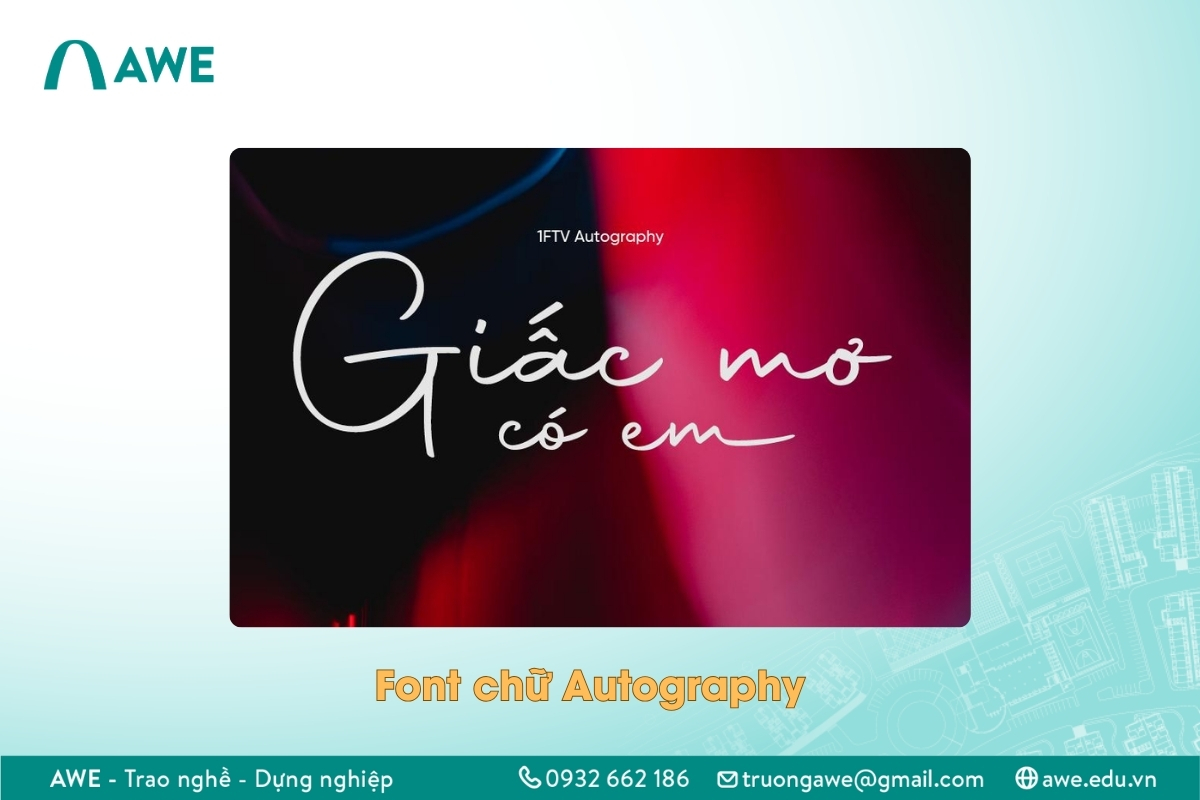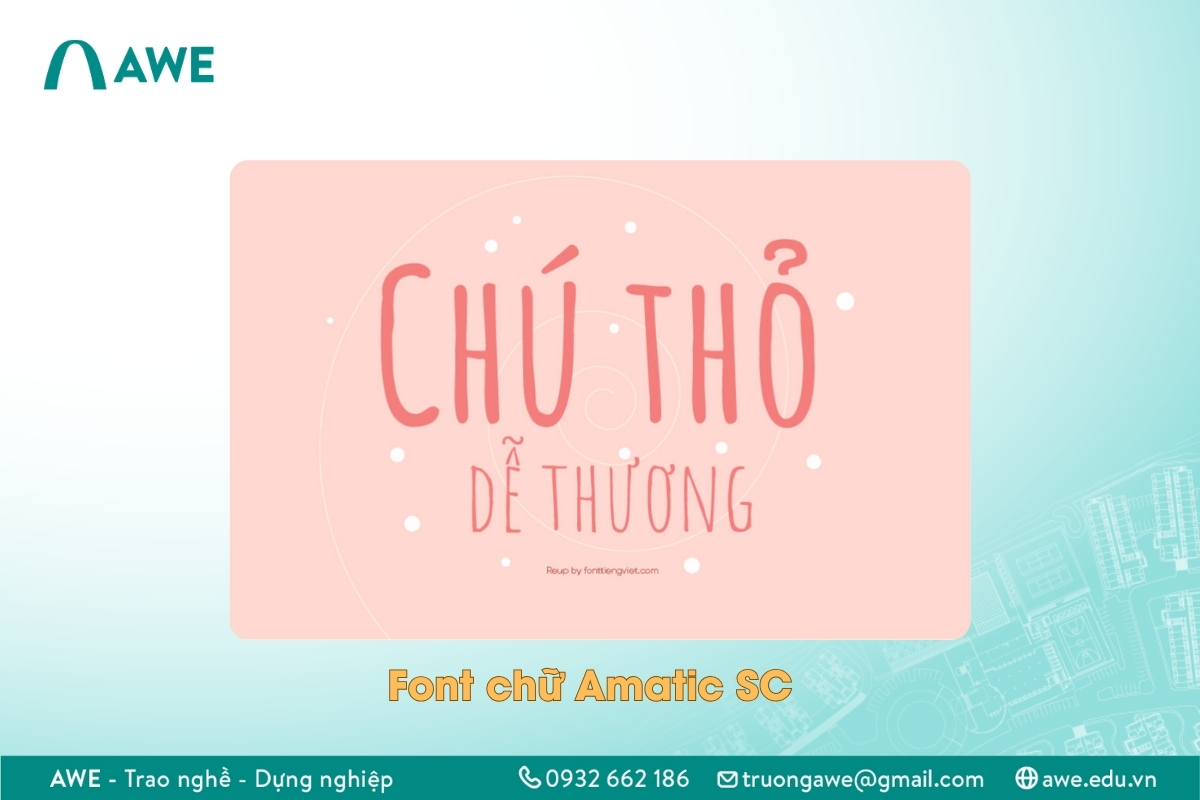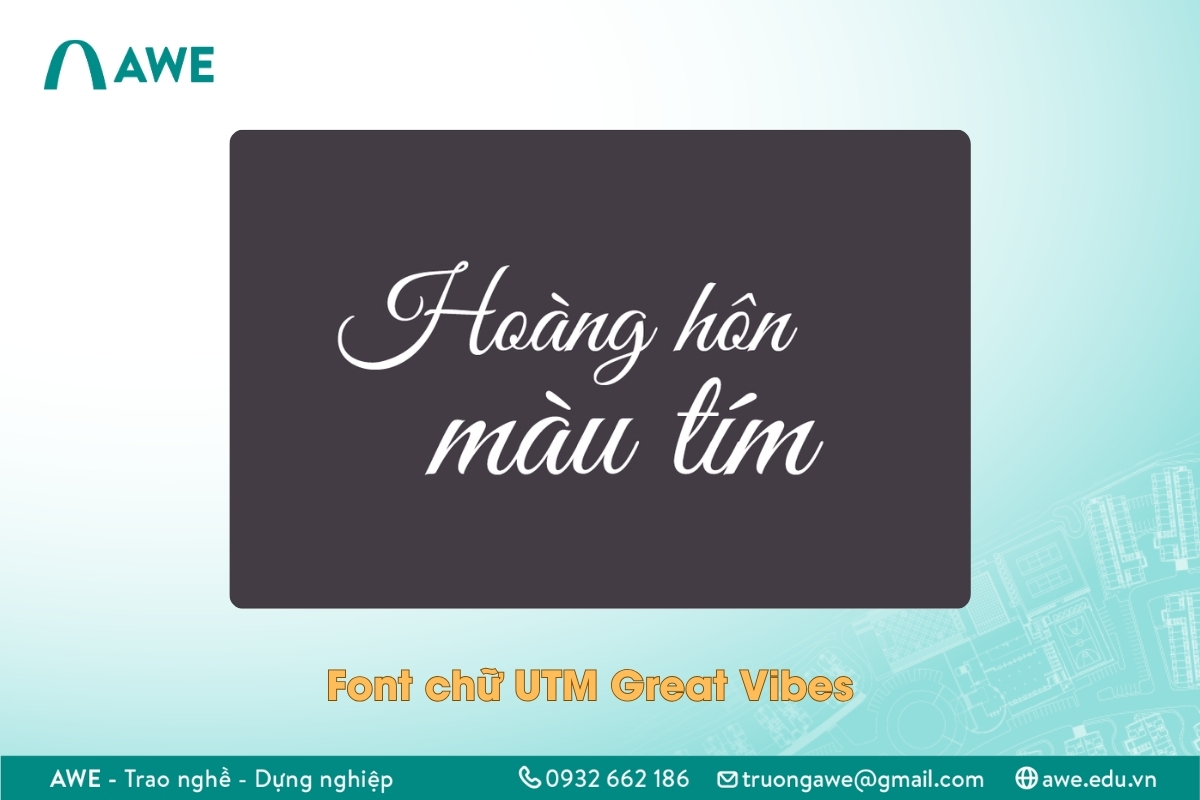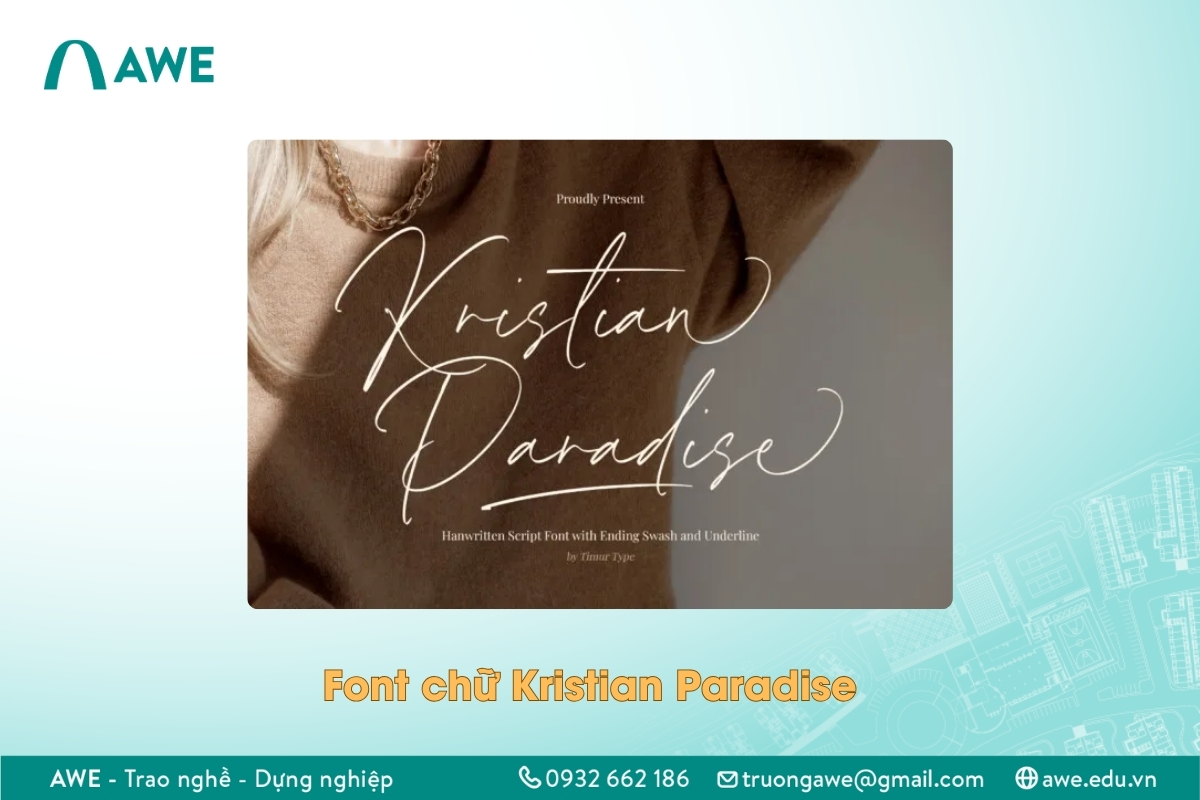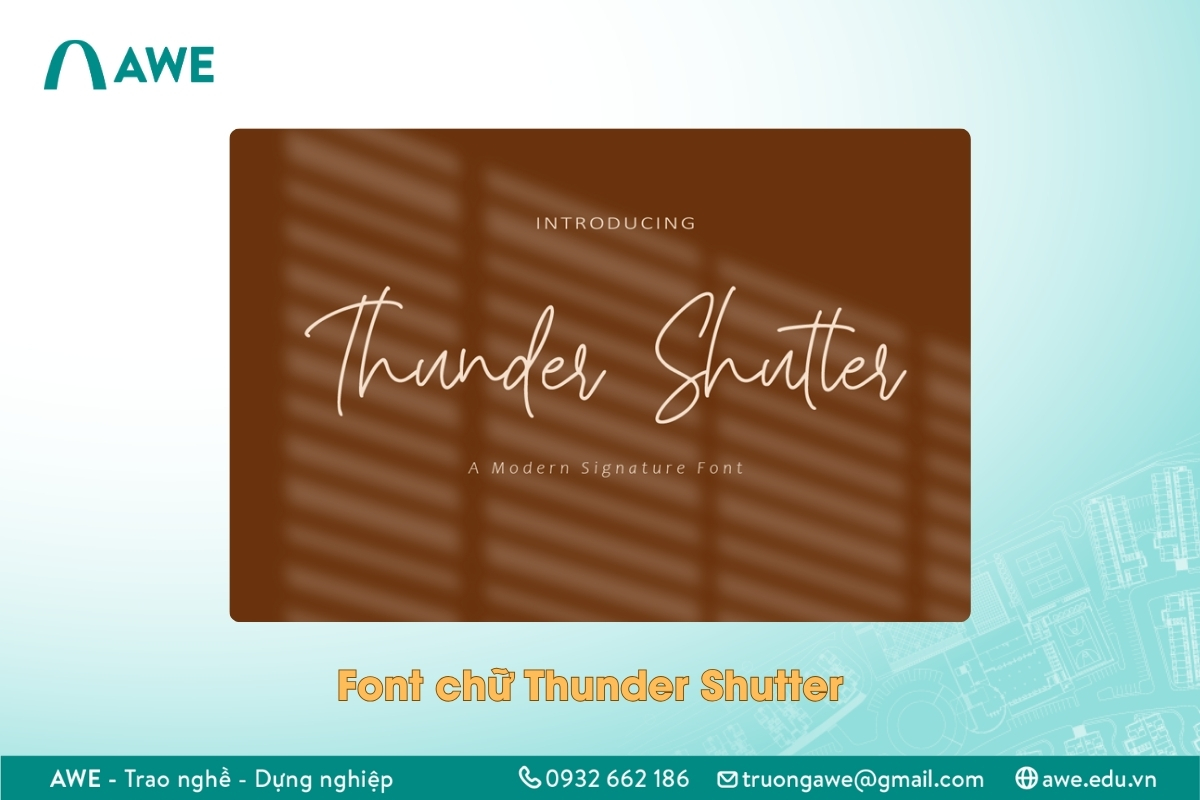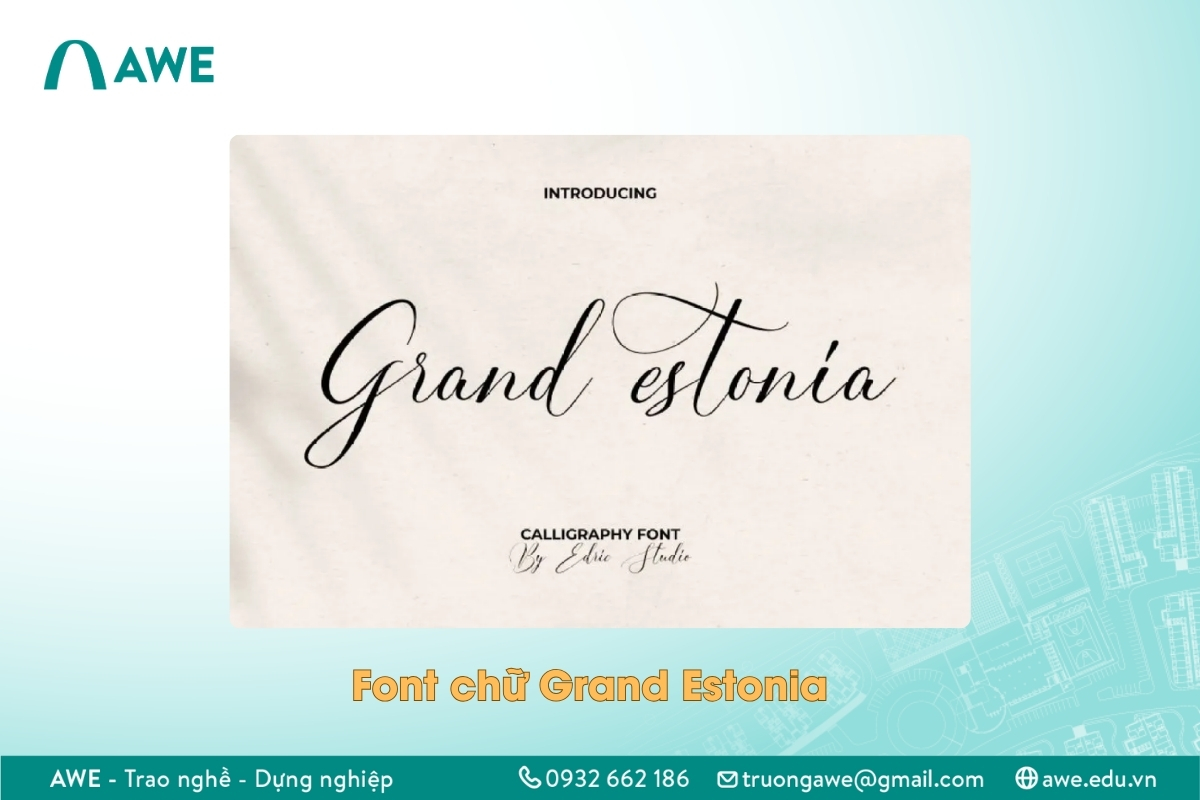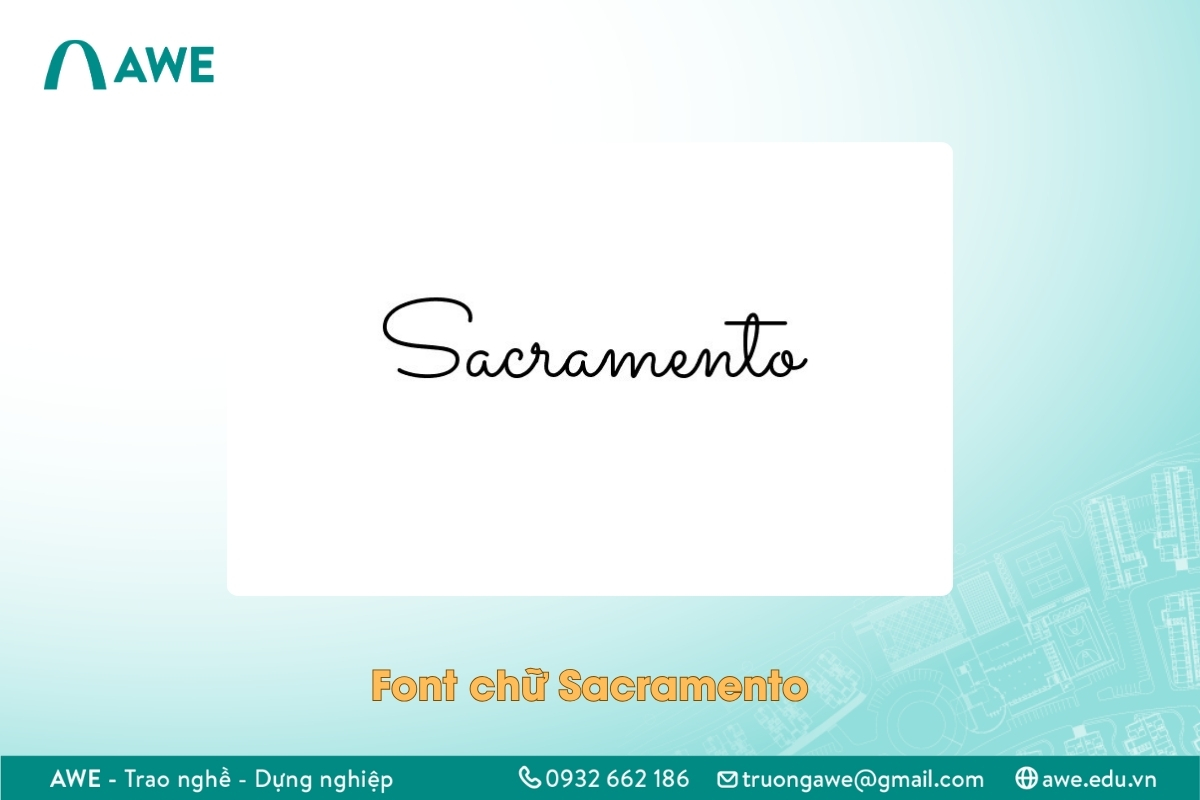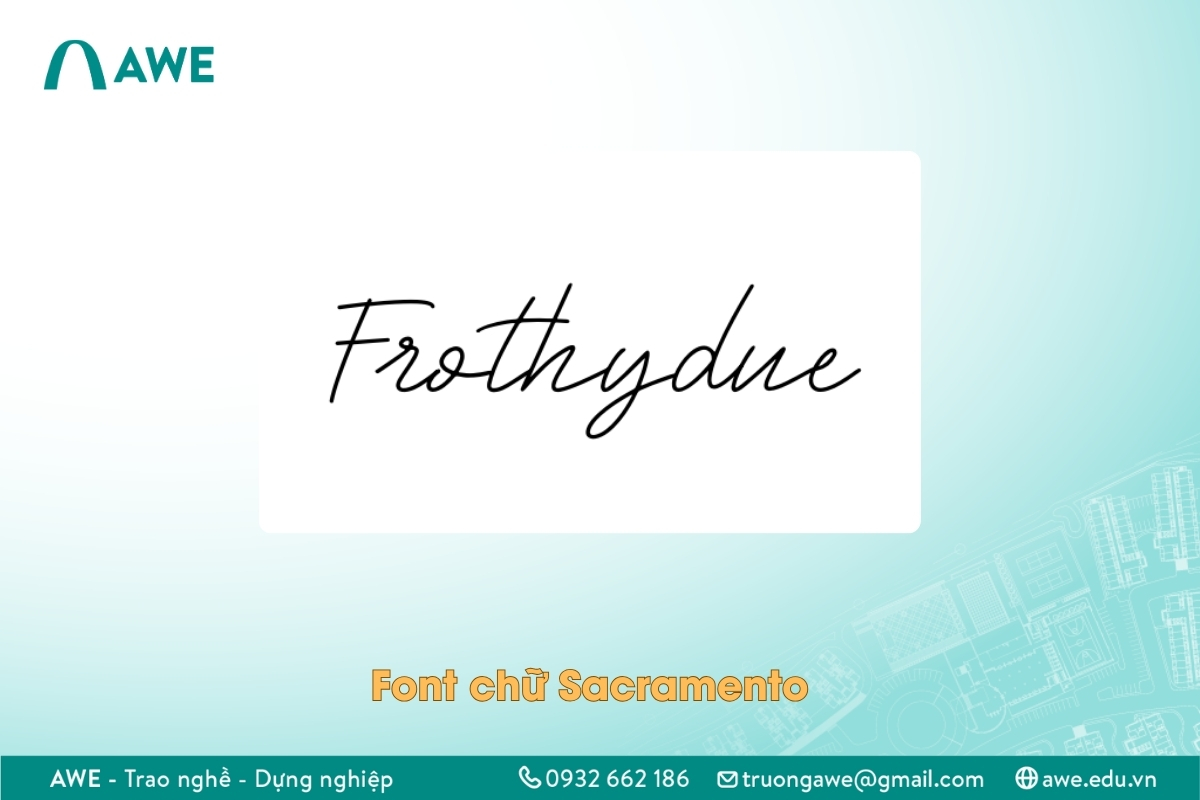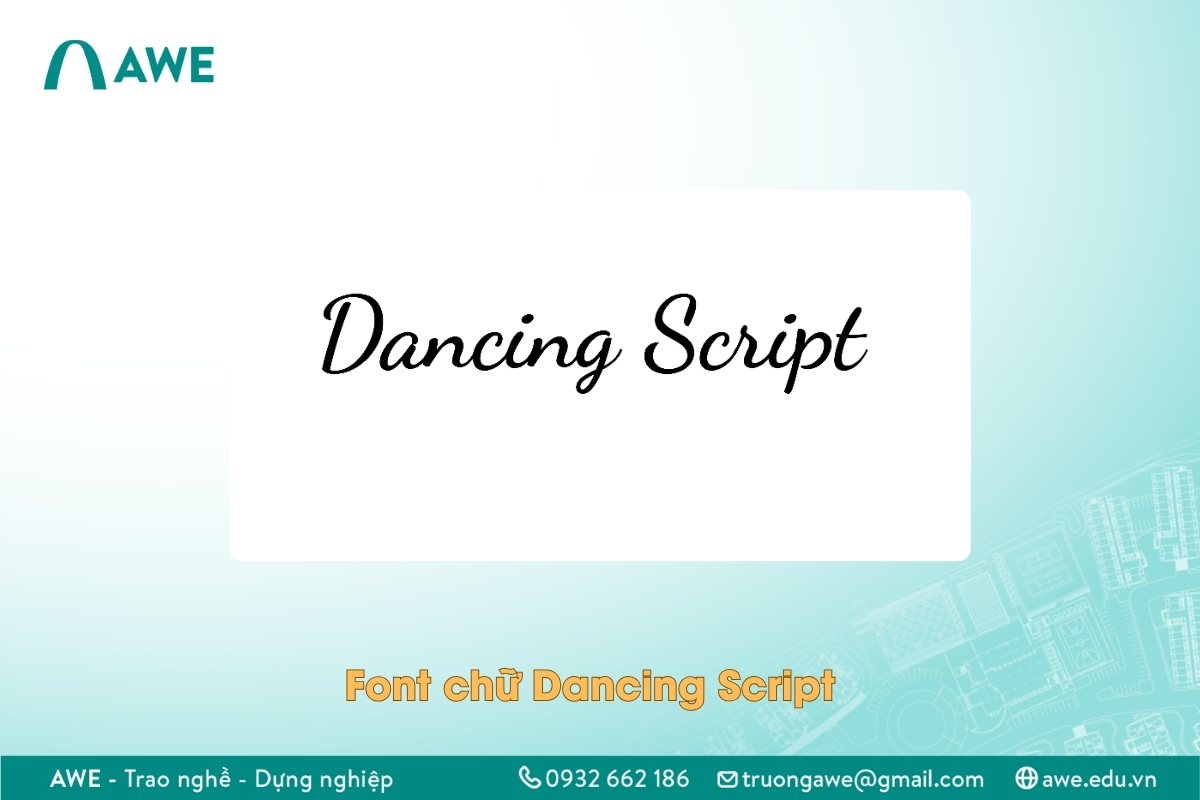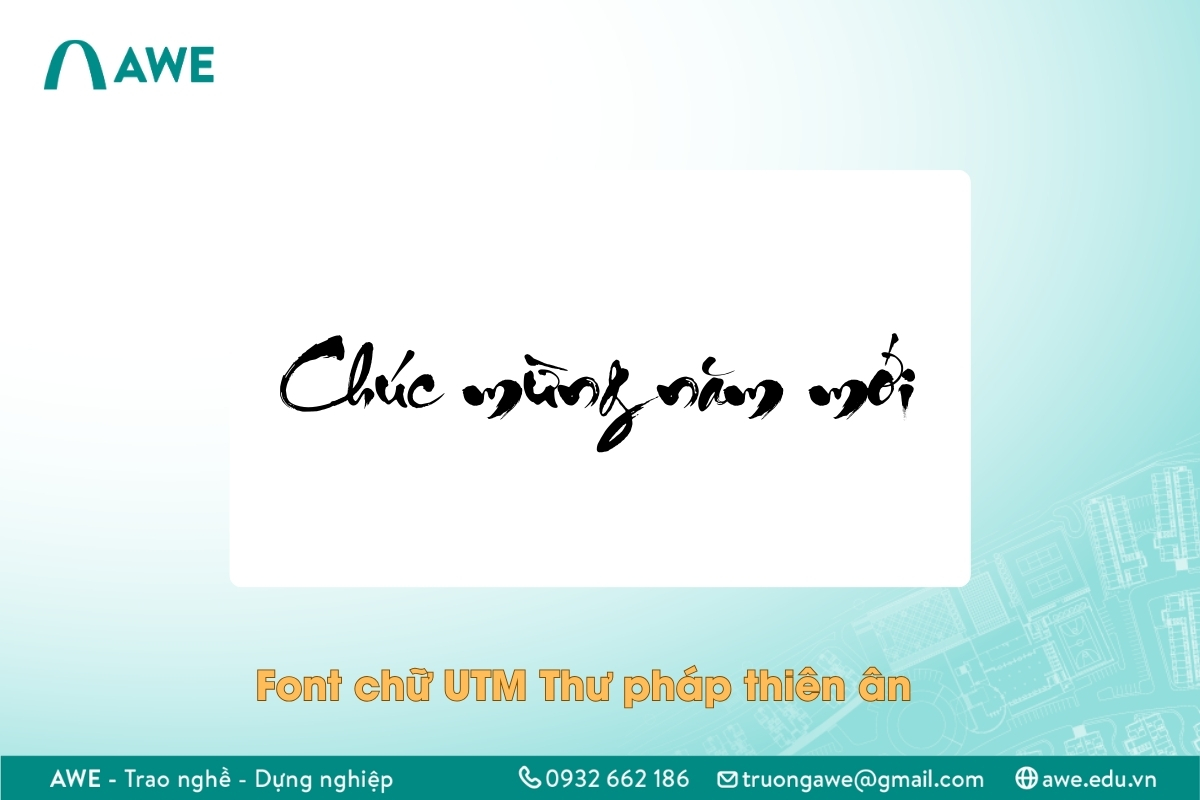
Gợi ý 15+ font chữ viết tay Việt hóa đẹp nhất năm 2025
15+ font chữ viết tay Việt hóa đẹp nhất dành cho dân thiết kế
Font chữ viết tay là những kiểu chữ mô phỏng nét bút tự nhiên của con người, mang tính phóng khoáng và giàu cảm xúc. Nếu bạn đang tìm kiếm những font chữ viết tay Việt hóa đẹp cho thiết kế thì tham khảo ngay bài viết dưới đây của AWE.
1. Khi nào nên dùng font chữ viết tay?
Font viết tay bao gồm nhiều phong cách khác nhau, từ thư pháp truyền thống đến chữ ký hiện đại, từ đường nét mềm mại nữ tính đến dạng viết nguệch ngoạc ngẫu hứng.
Font chữ viết tay phát huy hiệu quả tối đa trong những thiết kế đòi hỏi sự mềm mại, cá tính hoặc truyền tải cảm xúc cá nhân. Các lĩnh vực như wedding design, branding sản phẩm thủ công, thời trang, ẩm thực hoặc các sản phẩm dành cho phụ nữ thường xuyên sử dụng font viết tay để tăng sự gắn kết cảm xúc với người xem.
Tuy nhiên, vì nét chữ viết tay thường mang tính trang trí nên không phù hợp để dùng cho đoạn văn dài. Nhà thiết kế cần chú ý kết hợp font viết tay với một font sans-serif trung tính để tạo điểm nhấn mà vẫn giữ được sự dễ đọc. Bạn có thể tham khảo thêm font chữ không chân để biết cách phối hợp hiệu quả giữa hai nhóm font này.
2. 11 font chữ viết tay Việt hóa đẹp và cảm xúc
2.1 Font chữ Dancing Script Font cổ điển
Dancing Script là một font chữ viết tay mang phong cách cổ điển của những năm 1950, với nét cong uyển chuyển, thanh thoát. Font này thích hợp cho các thiết kế mang hơi hướng retro, nữ tính hoặc cảm xúc nhẹ nhàng như thiệp mời, bao bì mỹ phẩm, tiêu đề blog hoặc các trích dẫn truyền cảm hứng. Khi được Việt hóa, Dancing Script vẫn giữ được độ mềm mại cần thiết để thể hiện sự duyên dáng trong thiết kế hiện đại.
Font chữ viết tay Dancing Script
2.2 Font chữ viết tay UTM Thư Pháp Thiên Ân
Đậm chất văn hóa Á Đông, UTM Thư Pháp Thiên Ân là font chữ thư pháp được Việt hóa rất phổ biến trong các thiết kế truyền thống. Nét chữ phóng khoáng, mạnh mẽ và giàu chất thơ khiến font này được yêu thích trong các ấn phẩm Tết, câu đối, tranh thư pháp kỹ thuật số hoặc các thiết kế sự kiện văn hóa. Font phát huy tốt nhất khi được dùng làm tiêu đề chính, trên nền đơn sắc hoặc thiết kế mang màu sắc dân tộc.
Font chữ thư pháp UTM Thư pháp thiên ân
2.3 Font chữ viết tay Loveya Script bay bổng
Loveya Script là một font calligraphy hiện đại, mềm mại và bay bổng. Với các nét nối uyển chuyển, Loveya rất phù hợp với các thiết kế thiệp cưới, thương hiệu nữ tính, sản phẩm handmade hoặc các bài typography lãng mạn. Khi sử dụng Loveya, designer cần kết hợp với layout tinh giản và background nhẹ nhàng để font phát huy tối đa sự thanh thoát trong thị giác.
Font chữ viết tay Loveya Script
2.4 Font chữ UTM Dream Script cách điệu
UTM Dream Script mang vẻ đẹp của chữ viết tay cách điệu, có phần nghiêng nghiêng, bay bổng. Font này rất thích hợp để dùng cho các thiết kế trích dẫn, thơ văn, bìa sách hoặc thiệp chúc mừng. Đặc biệt, Dream Script giúp truyền tải sự dịu dàng, hoài niệm và tạo chiều sâu cho các sản phẩm đồ họa mang yếu tố cảm xúc.
Font viết tay UTM Dream Script
2.5 Font chữ viết tay Patrick Hand
Patrick Hand là font chữ viết tay mô phỏng nét chữ của người viết bằng tay thông thường. Đây là lựa chọn lý tưởng cho các thiết kế mang tính cá nhân, gần gũi như nhật ký, portfolio cá nhân, thiết kế giáo dục, hoặc các sản phẩm cần sự chân thật và tự nhiên. Patrick Hand không quá hoa mỹ, phù hợp với phong cách giản dị, không hình thức nhưng vẫn đầy biểu cảm.
Font viết tay Patrick Hand
2.6 Kiểu chữ SVN Lemon Tuesday cá tính
SVN Lemon Tuesday mang cá tính mạnh với các nét viết tự do, có phần ngẫu hứng và nổi loạn. Font này rất phù hợp với các thiết kế typography nghệ thuật, bìa album, poster cá nhân, hoặc sản phẩm dành cho giới trẻ. Khi dùng Lemon Tuesday, designer nên để font làm tâm điểm, tránh nhồi nhét nhiều yếu tố đồ họa khác để giữ được tinh thần phóng khoáng.
Font chữ viết tay đẹp UTM Lemon Tuesday
2.7 Font chữ UTM Ông Đồ Già hoài cổ
Lấy cảm hứng từ nét thư pháp truyền thống Việt Nam, UTM Ông Đồ Già mang đến không khí Tết, hoài cổ và đậm chất văn hóa. Font thường được sử dụng trong thiết kế lịch, tranh thư pháp, bao lì xì hoặc các chiến dịch truyền thông liên quan đến văn hóa Việt. Đây là font rất độc đáo, không dễ thay thế, phù hợp để tạo điểm nhấn đặc biệt.
Font chữ thư pháp UTM Ông đồ già
2.8 Font chữ Việt hóa Selima cá tính
Selima là font viết tay có đường nét mạnh mẽ, cá tính và hơi nghiêng về kiểu chữ vẽ tay (brush script). Font này phù hợp với thiết kế tiêu đề cá tính, poster thời trang, branding ngành làm đẹp, hoặc các dự án sáng tạo cần thu hút thị giác ngay từ dòng chữ đầu tiên. Với các thiết kế hướng đến phụ nữ hiện đại, Selima giúp thể hiện cá tính mà không quá phô trương.